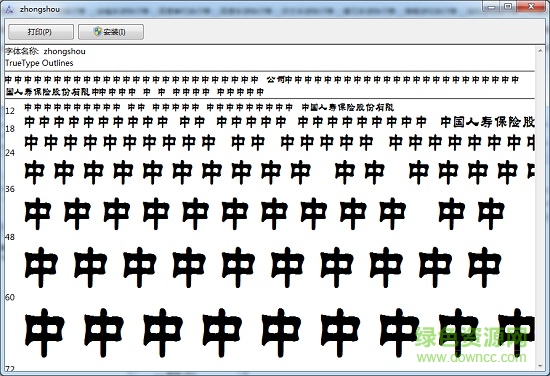
中国人寿保险字体是一款非常好用的字体,是中国人寿内部的一款字体,非常的刚劲有力,笔画清晰简洁,欢迎喜爱的朋友到绿色资源网下载使用!
字体中只包含“中国人寿保险股份有限公司”这几个字,使用时请输入0123456789AB这些字母,然后在字体列表里选择“zhongshou”,就可以输出这些字了。方便大家使用!